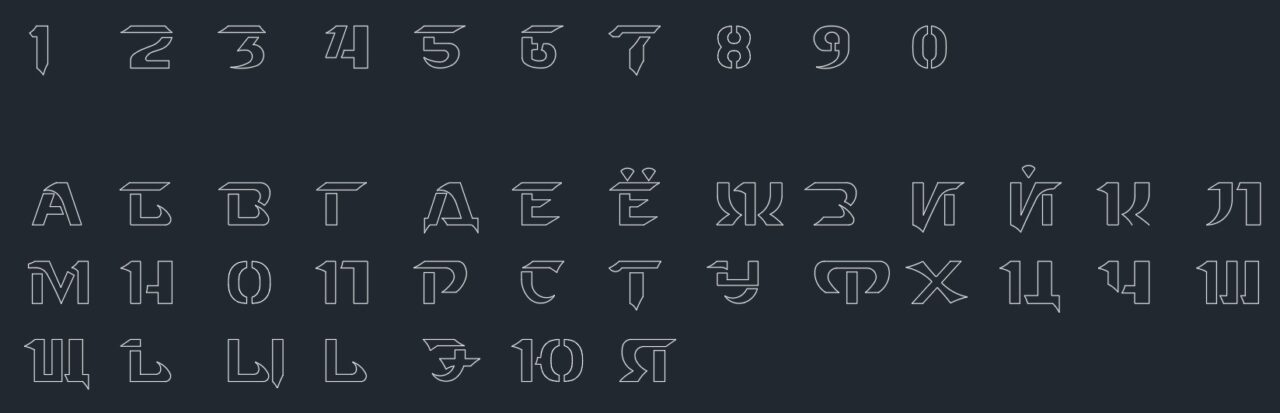
Шрифт можно использовать для резки листового металла на лазере или плазме. Подойдет для создания табличек с названием улиц и номерами домов
Шрифт трафаретный RusStarcraft